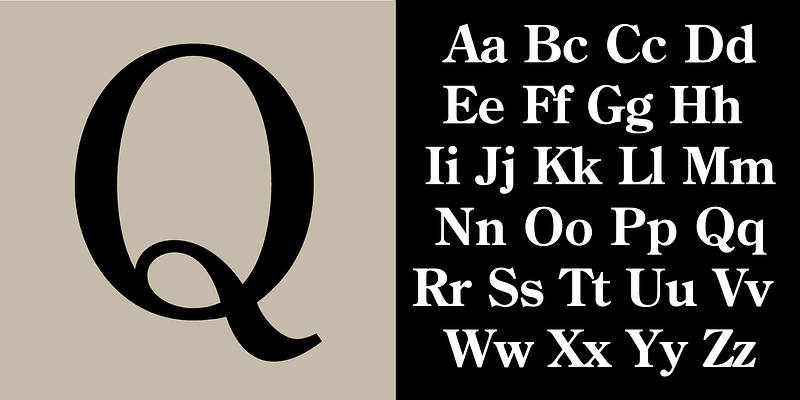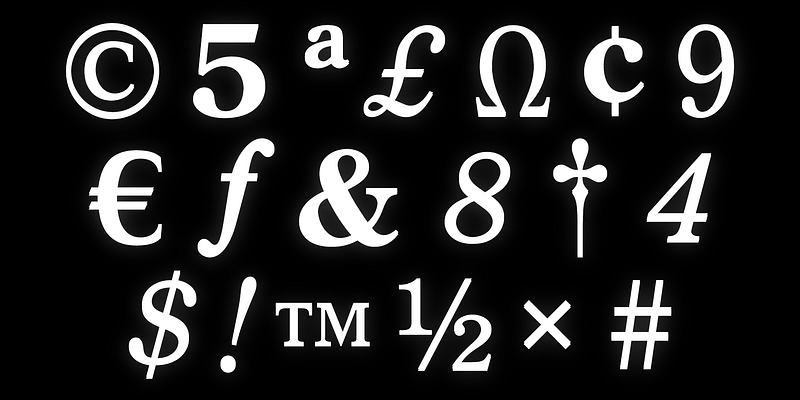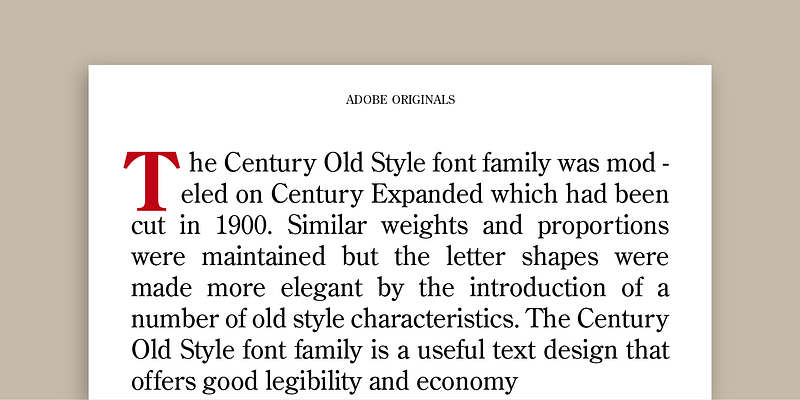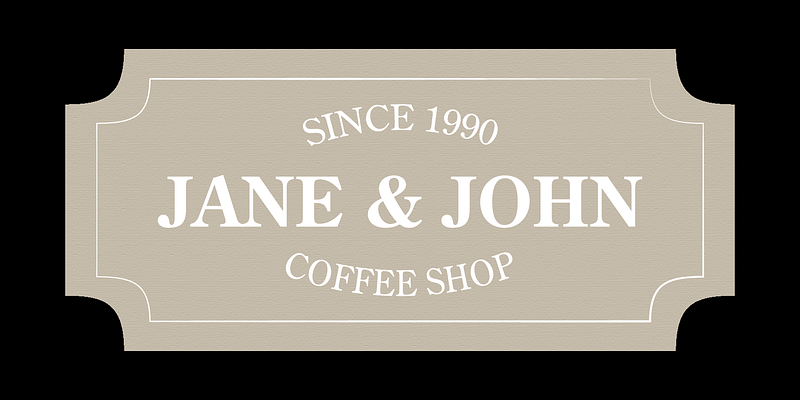
Century Oldstyle は、1908 ~ 1909 年に Morris Fuller Benton によってデザインされました。かなり大きな x ハイト、短いアセンダとディセンダ、大きな大文字は、「Century Expanded」のプロポーションを踏襲していますが、「Century Oldstyle」にはオールドスタイルのセリフを採用しています。「Century Oldstyle」は今もその読みやすさに定評があり、雑誌などの出版物に適しています。